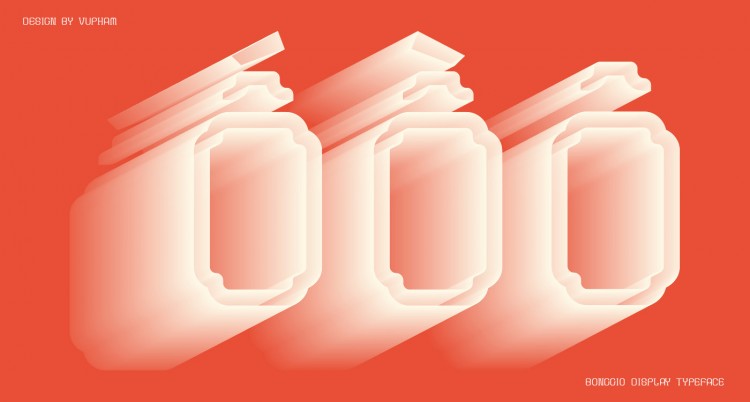
Giới thiệu về Font việt hoá Bong Gio Display
Trong thế giới thiết kế đồ họa hiện nay, việc lựa chọn một bộ Font Chữ phù hợp đóng vai trò quyết định đến tính thẩm mỹ của sản phẩm. Font việt hoá Bong Gio Display là một trong những bộ phông chữ độc đáo, mang phong cách hiện đại pha chút cổ điển, rất thích hợp cho các dự án sáng tạo. Với đường nét thanh thoát và bố cục cân đối, bộ phông này giúp truyền tải thông điệp một cách ấn tượng và rõ ràng nhất đến người xem.
Đặc điểm nổi bật của font chữ
Bong Gio Display sở hữu các đường nét uốn lượn tinh tế, tạo cảm giác mềm mại nhưng vẫn giữ được sự chắc chắn cần thiết. Khi được việt hóa, phông chữ này đã được tối ưu hóa các dấu câu tiếng Việt, giúp người dùng không còn gặp lỗi hiển thị khi soạn thảo văn bản. Đây là lựa chọn lý tưởng cho việc thiết kế tiêu đề sách, bìa tạp chí hoặc các biểu ngữ quảng cáo trong trường học.
Ứng dụng của Font việt hoá Bong Gio Display trong giáo dục
Đối với các bạn học sinh và giáo viên, việc sử dụng Font việt hoá Bong Gio Display sẽ giúp các bài thuyết trình hay báo cáo trở nên sinh động hơn. Sự kết hợp giữa tính nghệ thuật và sự rõ ràng giúp nội dung học tập dễ tiếp thu và bắt mắt. Bạn có thể dùng phông chữ này để làm thiệp chúc mừng, thiết kế nhãn vở hoặc trang trí bảng tin lớp học một cách sáng tạo nhất.
Kết luận về bộ font chữ độc đáo